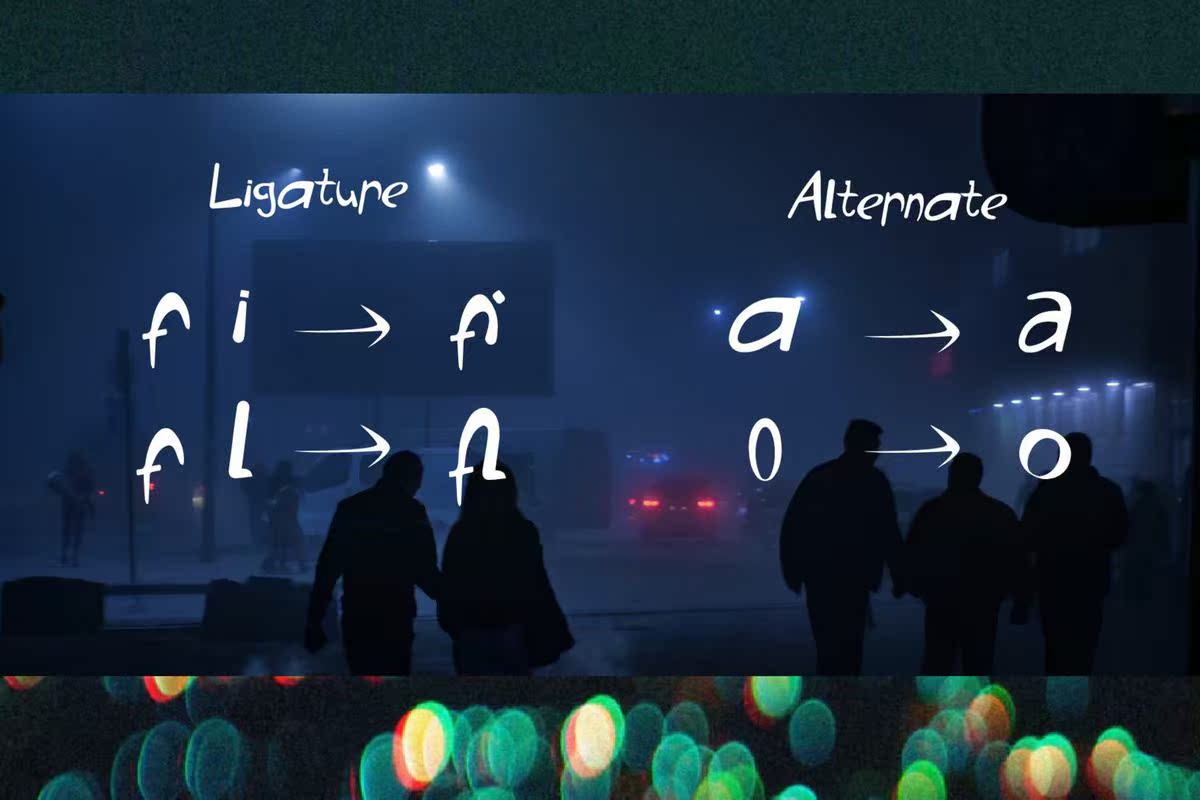
电影是一个充满活力的主题。这是因为我们在看完一部好电影后,在每一个伟大的电影时刻都会感受到治疗的刺激。这个主题是特别为你们制作的,在你的创意项目中,设计师总是为感伤而努力。电影是一种生动的主题。这是由我们在观看好电影后在每一个伟大的电影时刻所产生的治疗感受所激发的。这是一种特别为你的创意项目中的感伤而努力的力量。